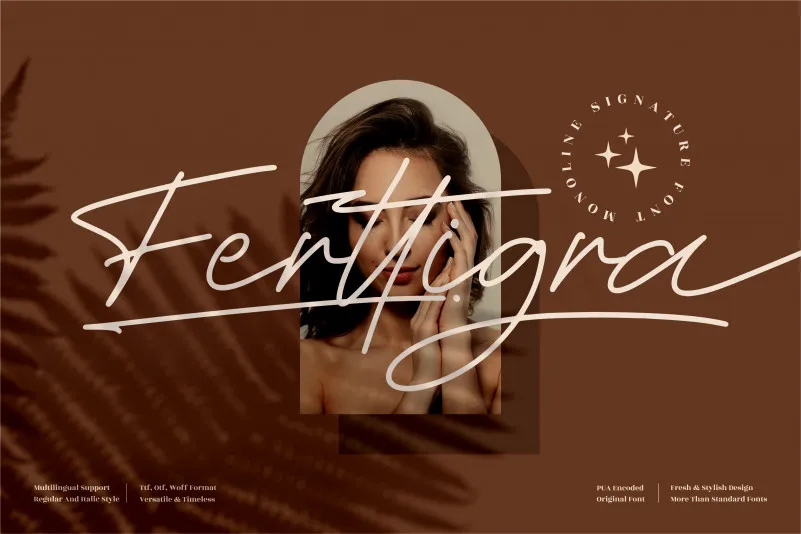
Ferttigra Font – Download Grátis
Esta é uma linda e refinada fonte de escrita manuscrita. Ela adere a um estilo elegante e moderno que se adequa perfeitamente para várias aplicações, desde logotipos e identidade visual até convites e assinaturas personalizadas. Seu design classe e sofisticado torna-a perfeita para diferentes ambientes, inclusive para os postais de casamento ou as redes sociais. Esta fonte é PUA encoded, o que significa que você pode acessar todos os símbolos e gírias com facilidade. A perspectype criou a Ferttigra Font, uma fonte de escrita manuscrita perfeita para designers que buscam uma opção elegante e sofisticada. Ela combina modernidade e estilo clássico para oferecer flexibilidade em diversas aplicações gráficas. Seja você um designer profissional ou iniciante, a Ferttigra é uma excelente escolha.